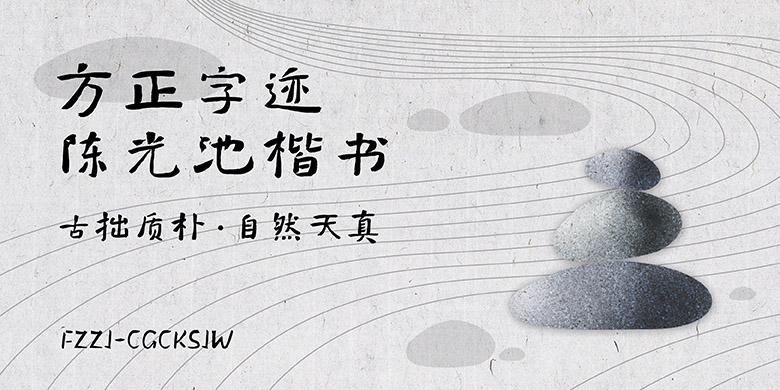
方正字迹-陈光池楷书-简繁
楷书是书法中为大众所欢迎喜爱的一种字体,如何把自己的楷书写得特色明显,富有变化,是作者必须面对和重点思考的问题。陈光池初习唐楷,对褚、欧、颜、柳等诸体均有研习涉猎,后又钟情魏晋墓志,更兼习汉隶摩崖,把汉隶的一些笔法融入楷书之中。方正字迹-陈光池楷书,书写既要有师古之迹,更要有造化之功:既体现古拙、质朴、端庄、浑厚的面目,更散发稳中求变、自然天真、楷而不板、正而活泼的风貌;尤其注重沉稳刚健的品格和自信自强、勇于探索的精神融铸笔端。只有这样,楷书才会给人带来端凝雄健以及淳朴和谐之美的享受。